أحد الجوانب المهمة التي تجذب انتباه زوار الموقع هو الطباعة. لا يساعد تحديد الخط المناسب في التعبير عن رسالتك فحسب ، بل يمكن أن يؤثر أيضًا على صورة علامتك التجارية ويجعل علامتك التجارية أكثر قابلية للتحديد.
في هذه المقالة ، سأقدم لك أفضل الخطوط التي يمكنك استخدامها لمتجر Shopify الخاص بك وبعض الأخطاء التي يجب عليك تجنبها عندما يتعلق الأمر باختيار الخط. الآن دعنا نقفز مباشرة إلى التفاصيل.
لماذا الخطوط مهمة لمتجر Shopify الخاص بك
من المفاهيم المهمة التي يجب وضعها في الاعتبار عند إنشاء موقع ويب للتجارة الإلكترونية "الحد الأدنى من تكلفة التفاعل". هذا هو الحد الأدنى من الجهد اللازم لتقرير ما إذا كان جزء من المحتوى يستحق القراءة. اكتشفت دراسة أجرتها مجموعة Nielsen / Norman أنه ، في المتوسط ، يقرأ المستخدمون فقط 28 بالمائة من الكلمات على موقع الويب كحد أقصى. تختلف النسبة قليلاً حسب عدد النسخ على الموقع. ومع ذلك ، إلى جانب حقيقة أن معظم الناس يقضون 15 ثانية في المتوسط على صفحة الويب ، فإن الإحصائيات تعزز الحقيقة البسيطة: كل كلمة تحتاج إلى أن يتم حسابها بعناية.
هذا هو المكان الذي تلعب فيه الخطوط دورًا مهمًا. عند استخدامها بشكل صحيح ، ستساعد الخطوط القارئ على الانخراط ، وجعله يرغب في البقاء لفترة أطول على موقع الويب الخاص بك ، ونأمل أن يقود العميل خلال عملية الشراء بنجاح.
أفضل خط لمتجر Shopify الخاص بك
الآن دعنا نراجع الخطوط التي يمكنك استخدامها لمتجر Shopify الخاص بك. ضع في اعتبارك أن هذا لا يعني أنه لا يمكنك استخدام أي خطوط أخرى خارج هذه القائمة ، ولكن هذه الخطوط هي فقط الأكثر شيوعًا وسهولة في القراءة.
هيلفيتيكا
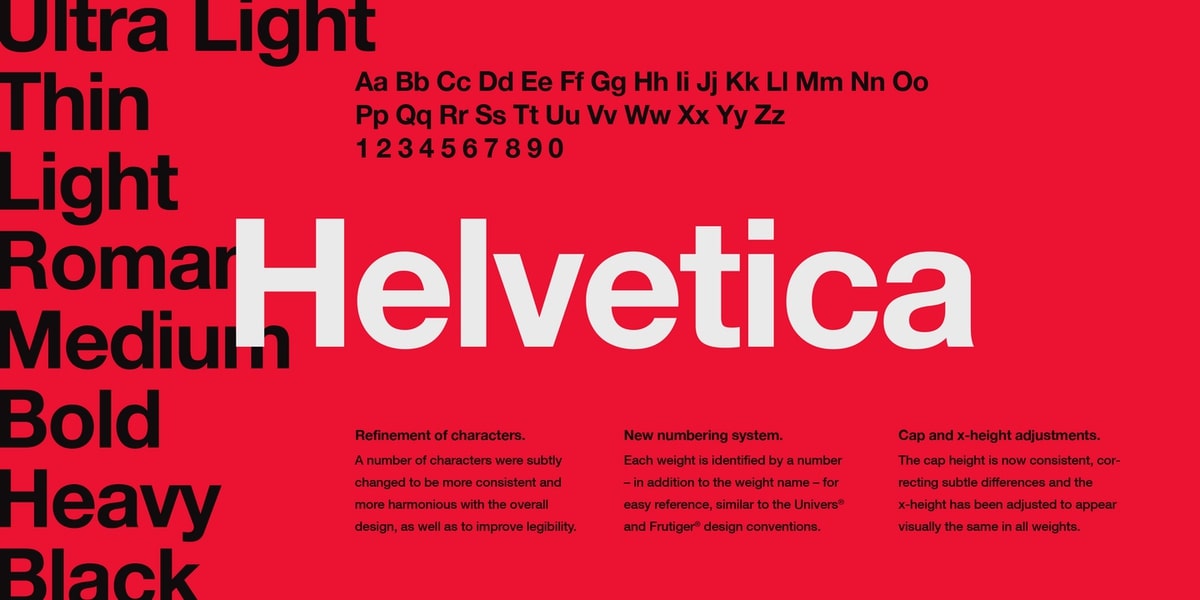
هلفتيكا قديمة. لقد كان موجودًا منذ عام 1957. إنه جزء من عائلة sans-serif ، لذلك لا تحتوي الحروف على منحنيات في نهاية كل ضربة. إنه خط كلاسيكي ، وهو الآن مقسم إلى أنواع مختلفة ، مثل Helvetica light ، و round ، والمزيد. Helvetica بسيط وشائع الاستخدام من قبل الشركات الكبرى لشعاراتها وموادها التسويقية.
جاراموند
Garamond قديم أيضًا ، وله شعور قديم به. إنه مثالي للنص الأساسي في الكتب المطبوعة ، ويمكن أيضًا قراءته بسهولة. باستخدام هذا الخط ، سيكون لموقع الويب الخاص بك مظهر كلاسيكي ، وقد يبدو كل حرف وكأنه نقش لبعض الأشخاص.
اريال
ربما يكون Arial هو الخط الأكثر أمانًا للاستخدام ، وهو إلى حد كبير القاعدة في عالم الطباعة. في بعض الأجهزة أو معالجات النصوص ، يُطلق على Arial اسم Arial MT. إنها متطابقة دون أي تغييرات ملحوظة.
هناك العديد من الأنواع الفرعية لهذا الخط ، ولكن يسهل قراءتها جميعًا. إنه ينتمي إلى عائلة خط sans-serif. تعني كلمة Sans serif عدم وجود أسطر من أي نوع في نهاية كل حرف. الشيء الإيجابي في هذا الخط أنه مألوف ، وجميع أجهزة Microsoft توفره في نظام التشغيل. iOs و Android أيضًا ليس لديهما مشكلة في التعرف على هذا الخط.
عائلة الساعي
تتكون عائلة البريد السريع من قسمين - البريد السريع والبريد السريع. اليوم ، النسخة الأكثر شعبية هي الأخيرة. الخط سهل القراءة لأن جميع الأحرف متباعدة بشكل متساوٍ. العديد من الخطوط لها عرض أوسع ، لكن ليس هذا العرض. هذه هي الطريقة التي صممها هوارد كيتلر في عام 1955.
تعرف كل من أجهزة الكمبيوتر والمتصفحات عائلة البريد السريع ، ولن يتم إجراء أي تعديلات إذا قاموا بفتح موقع ويب باستخدام هذا المحرف. لقد كانت موجودة منذ عقود. تم استخدامه في الأصل في الآلات الكاتبة لشركة IBM ، ولكن لاحقًا شوهد على نطاق واسع في أجهزة الكمبيوتر الشخصية أيضًا.
فيردانا
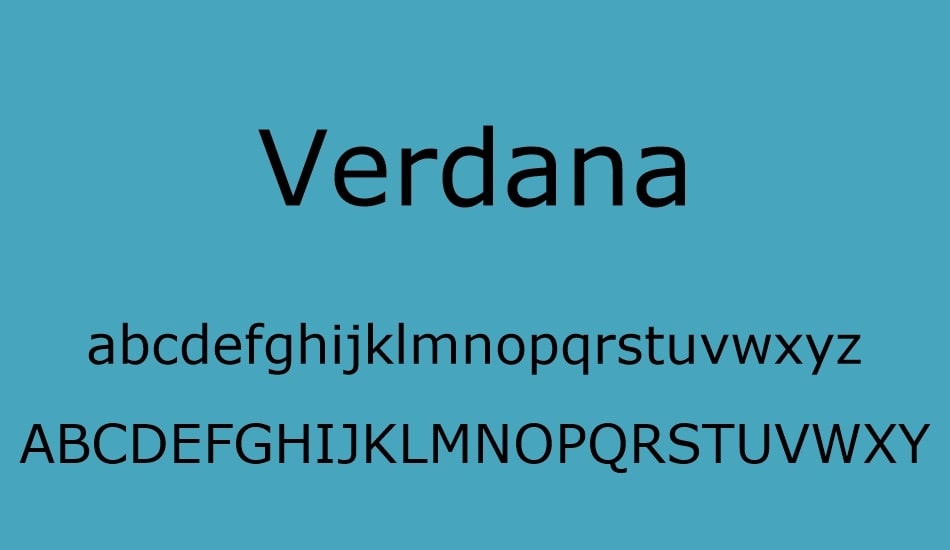
يعتبر العديد من خبراء الخطوط Verdana بمثابة خط ويب حقيقي. إنه خط عادي بلا رقيق ، كبير بما يكفي للقراءة السريعة. إذا نظرت عن كثب ، فستجد أن الأحرف مستطيلة قليلاً ، مما يسهل قراءتها من أجهزة الكمبيوتر المحمولة والأجهزة اللوحية والهواتف الذكية. تركز Verdana الآن على الأجهزة المحمولة وأجهزة الكمبيوتر. وهي محقة في ذلك ، حيث تم تطويرها من أجل Microsoft ومن قبلها.
تايمز نيو رومان
هذا الخط هو اختلاف طفيف في خط Times (أحد أقدم الخطوط). تستخدم على نطاق واسع في الصحف والمجلات في جميع أنحاء العالم ، ويمكن التعرف عليها بسهولة. تمت كتابة العديد من الكتب أيضًا بهذا الخط ، ولن يجد الأشخاص من جميع أنحاء العالم صعوبة في القراءة.
والسبب في تسميتها Times هو أن الشركة التي أنشأت هذا الخط كانت Time Magazine في عام 1931. وبينما لم تعد المجلة مستخدمة ، إلا أنها لا تزال شائعة الاستخدام كنص أساسي في منشورات الكتب الإعلانية في الصحف.
بوكمان
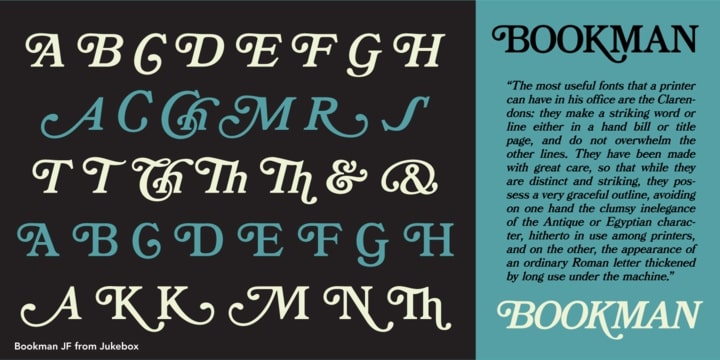
Bookman يشبه Times New Roman. ومن المعروف أيضًا باسم Old Style Bookman. لقد تم استخدامه على نطاق واسع للطباعة التجارية وطباعة العرض. كان شائعًا جدًا في الستينيات ، ولكن يمكن إرجاع جذوره إلى خمسينيات القرن التاسع عشر. Bookman مثالي كرأس ، ولكن يمكنك أيضًا استخدام إصدار أرق للنص الأساسي.
Trebuchet MS
هذا الخط له إحساس القرون الوسطى به. بطريقة ما ، يعطي للقارئ إحساسًا بالقلاع القديمة حيث يعيش الأثرياء. تم تطويره بواسطة Microsoft وتم إصداره لأول مرة في عام 1996. تم تطويره أيضًا للإنترنت ، ولهذا السبب أطلق عليه اسم trebuchet. كان المنجنيق عبارة عن محرك حصار من العصور الوسطى أطلق مقذوفات عملاقة. ولأنه كان سيتم إطلاقه على الإنترنت ، فقد تم تسمية الخط بهذا الاسم.
كامبريا
هذا واحد لديه العديد من أوجه التشابه مع Trebuchet MS. يبدو جميلًا ويتم استخدامه بشكل أفضل إذا كنت لا تريد استخدام Calibri. إنه جزء من عائلة serif ، مما يعني وجود بضعة أسطر في أطراف الحروف. ومع ذلك ، فمن المعروف أيضًا أنه نوع بسيط من الخطوط. من الأفضل استخدام Cambria كوثيقة أساسية ، حيث يسهل قراءتها بشكل كبير حتى عندما تكون صغيرة.
خط بالاتينو
هذا الخط قديم جدًا ، ويمكننا تتبع تاريخه إلى القرن الرابع عشر. إنه أسلوب واسع ، لذا فهو قابل للقراءة. تم تطوير خط Palatino الذي نعرفه هذه الأيام لأول مرة في عام 1949. عندما تم إنشاؤه ، تم تسميته على اسم سيد الخط الإيطالي ، Giambattista Palatino. تقليديًا ، كان هذا الخط يُستخدم فقط للرؤوس والإعلانات المطبوعة ولكنه يُستخدم الآن غالبًا للنص الأساسي ، لا سيما في الكتب الإلكترونية.
تأثير
هذا هو الخط المفضل للعناوين. إنه كثيف ، وجريء ، وسريع القراءة ، ويشكل عنوانًا رئيسيًا. الخط هو الأفضل للعناوين والعناوين الفرعية ، ولكن ليس للنص نفسه. إذا تم استخدامه كثيرًا ، فإن سُمك الخط يمكن أن يجعل من الصعب قراءته. من الأفضل استخدامها لإعلان صفقة أو استخدامها لجذب انتباه المشاهدين في إعلاناتك.
كاليبري
هذا الخط حديث جدًا لأنه تم طرحه فقط في عام 2004 وتم إتاحته للعالم في عام 2007. تم تقديمه للعالم بواسطة Microsoft واستبدل Times New Roman باعتباره الخط الافتراضي لـ Microsoft Word ومنتجات MS Office الأخرى. إنه مستدير ، لذا يسهل على العين قراءته. بينما يتم تقريبه ، فإنه لا يبدو كرسوم متحركة. يحافظ على مظهر رسمي ويعتبر نوعًا بسيطًا من الخطوط.
النحاس القوطي
هذا الخط به مسافات كبيرة بين الأحرف. تم تصميمه في عام 1901 ، واستخدم الفنان النقوش على الألواح النحاسية كأساس للتصميم. لهذا السبب ، يسهل قراءة الخط ويمكن استخدامه أيضًا كرأس عريض لمدونتك أو أسماء المنتجات الخاصة بك. هذا الخط هو الأفضل للرؤوس ويتم إقرانه بشكل أفضل مع الخطوط الغامقة الأخرى التي تحتوي على مساحة كبيرة مثل Verdana للنص الأساسي.
يتعلم أكثر:
- كيفية إضافة الخطوط إلى Shopify الموضوع؟
- كيفية تغيير الخط في صفحة الخروج على Shopify؟
أخطاء يجب تجنبها عند اختيار الخطوط لمتجر Shopify الخاص بك
تأكد من عدم تعقيد الخطوط الخاصة بك. يؤدي خلط الكثير من الخطوط والأنماط إلى صعوبة قراءة النص. غالبًا ما يزعج القارئ ويصرف انتباهه عن الرسالة التي تحاول إيصالها. عندما يتعلق الأمر باختيار الخطوط ، فالقليل هو الأكثر. إليك ما يجب عليك تجنبه:
لا تعبث بالنسب
أي شيء يمتد أو ينحرف في ضغط أو يتلاعب بنسب الخطوط ليست فكرة جيدة. فقط لا تحاول.
تجنب استخدام خط Comic Sans أو Papyrus
لسوء الحظ ، تم الإفراط في استخدام هذين الخطين بشكل كبير وسوء استخدامهما ، لدرجة أنهما الآن مرادفان لعدم الاحتراف. آخر شيء تريد القيام به هو جعل علامتك التجارية تبدو غير متطورة ومبتكرة.
الكلمات الأخيرة
قد يكون اختيار الخطوط المناسبة لمتجر Shopify عبر الإنترنت أمرًا صعبًا ، لكن مجموعة الخطوط في هذه المقالة ستساعدك في إنشاء أفضل مجموعة خطوط للويب الخاص بك. باستخدام سمات مثل اللون والطول والوزن والتصنيف ، يمكنك بناء ثنائي يناسب جيدًا معًا. لا تتردد في ترك التعليقات أدناه لمزيد من المناقشة حول هذا الموضوع. :-)